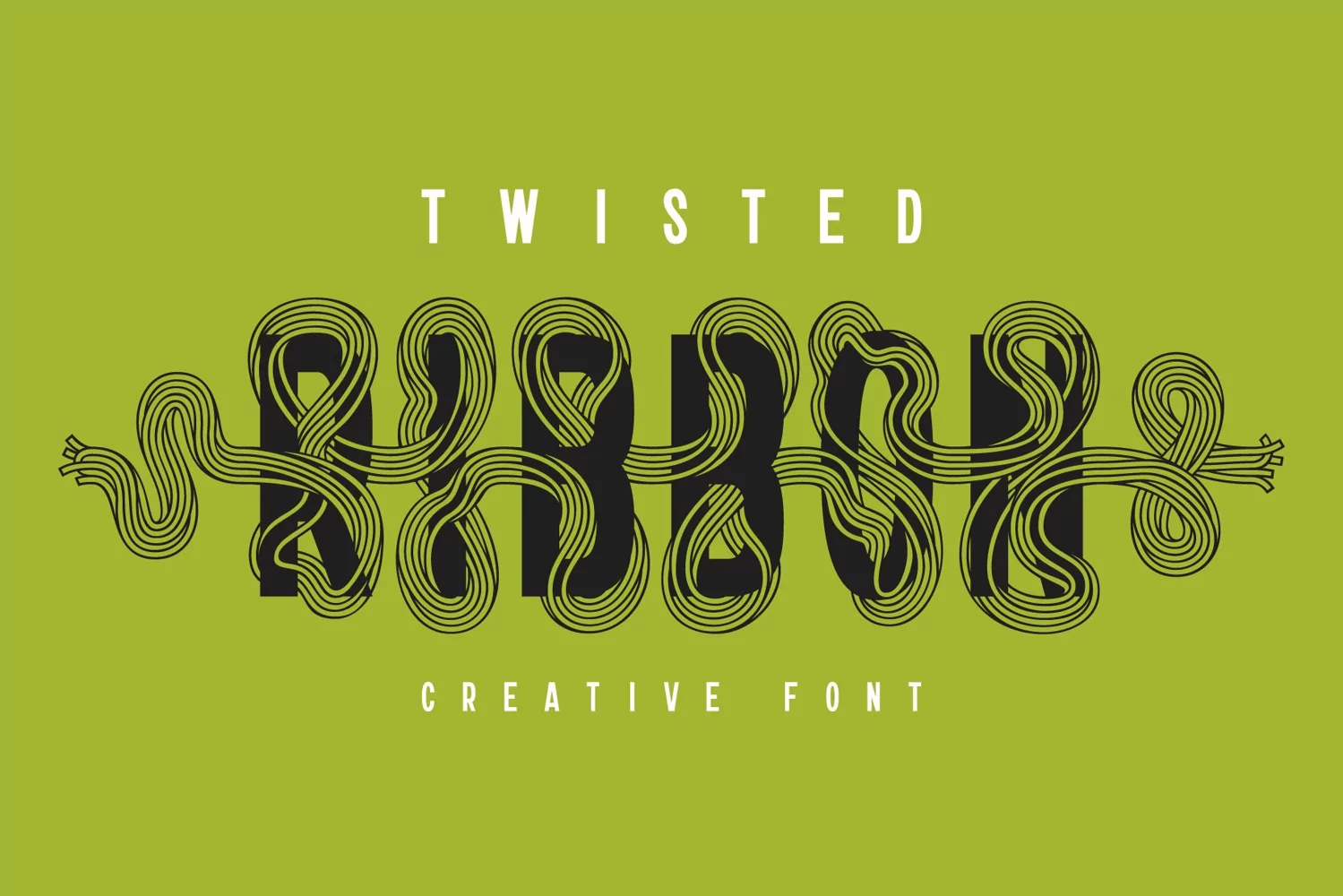
دانلود فونت Twisted Ribbon
سلام! ارائه یک مجموعه فونت خلاق – روبان پیچ خورده. این یک تایپ فیس تزئینی وکتور با خطوط منحنی است که دور حروف بافته شده است. شکل خطوط به گونه ای ساخته شده است که به طور یکپارچه از یک حرف به حرف دیگر جریان می یابد.
برای دستیابی به یک جلوه جالب، گلیف های اضافی مانند انتهای خطوط یا پسوند اضافی یک روبان به این فونت اضافه می شود. برای دسترسی به یک گرافیک اضافی، فقط یک خط زیر و یک کاراکتر مربوطه را از جدول ارائه شده تایپ کنید. با استفاده از ویژگی Ligatures OpenType، این متن به طور خودکار با عناصر پشتیبانی مناسب جایگزین می شود و یک جلوه روبان پیچ خورده یکپارچه ایجاد می کند (لطفا مطمئن شوید که ویژگی Standard Ligatures در نرم افزار شما پشتیبانی و فعال است).
همچنین، کاراکترهای ساده و بدون روبان در این فونت برای اکثر گلیف ها گنجانده شده است. فقط ویژگی Stylistic Alternates OpenType را برای دسترسی به آنها فعال کنید.